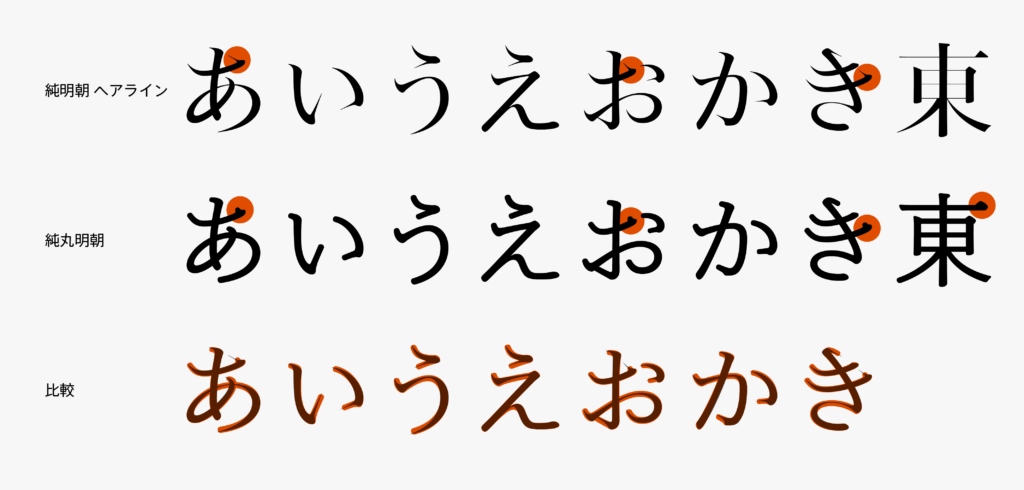
純丸明朝 開発ストーリー 1「仮名の脈絡」
純明朝と純丸明朝で骨格は同じですが、細部の設計方針には違いがあります。
純明朝では仮名の脈絡の長さが特徴的です。純明朝ヘアラインは特に鋭く長くなっており、筆の流れの優雅さにつながっています。引き締まった骨格とも相まって、クラシックな印象にも影響しています。
対して純丸明朝の特に細いウエイトでは、脈絡が純明朝よりも短く作られています。「あ、お、き」などの横画から縦の動きにつながる脈絡に顕著です。脈絡は次の筆画への繋がりで先が長く細くなっていく性質があるため、先端が丸く太い純丸明朝では短くなっています。加えて、漢字のウロコの形と調和する形に作られています。筆画細部の丸みや先端の厚みのぽってりとした特徴的な形を保ちつつ、その短さによって見え方がしつこくならない程よさになっています。